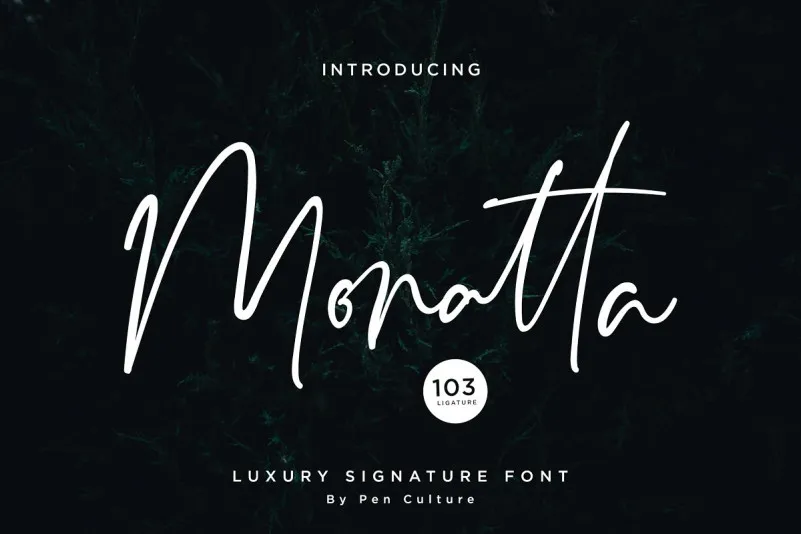
A Monatta Signature Font é uma elegante opção para designers que desejam dar um toque autêntico a seus trabalhos. Esta fonte foi projetada para oferecer aos criadores uma sensação de autenticação, trazendo uma verdadeira sensação de personalização às criações. É perfeita para branding pessoal ou qualquer tipo de projeto que exige uma presença visual única e memorável. Com sua abrangência em OpenType, a Monatta Signature Font oferece muitos recursos úteis aos designers. Esses incluem letras maiúsculas completas, suporte multilíngue (incluindo símbolos de moeda) e 94 ligaturas personalizadas, garantindo que seu texto seja fácil de ler e memorável para os usuários finais. Além disso, vem com um conjunto amplo de números estándar, tornando-a uma fonte versátil e muito simples de usar. Perfeita para qualquer tipo de projeto, a Monatta Signature Font é certamente o complemento perfeito para quem busca uma linguagem visual que se destaca. Não hesite em explorá-la – ela certamente fará sua marca.